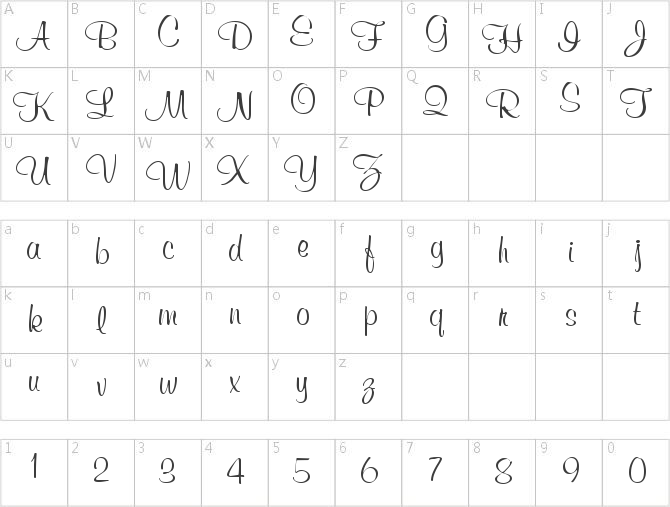
字體名稱: Murray
Murray Hill Bold
Murray Hill Bold介紹
Murray Hill Bold字體字庫是一款讓人賞心悅目、百看不厭的英文字體,適合各類廣告和產品包裝設計應用,字體大小0.05MB,格式為ttf字體,上傳用戶是15331803325,作者/版權方為未知